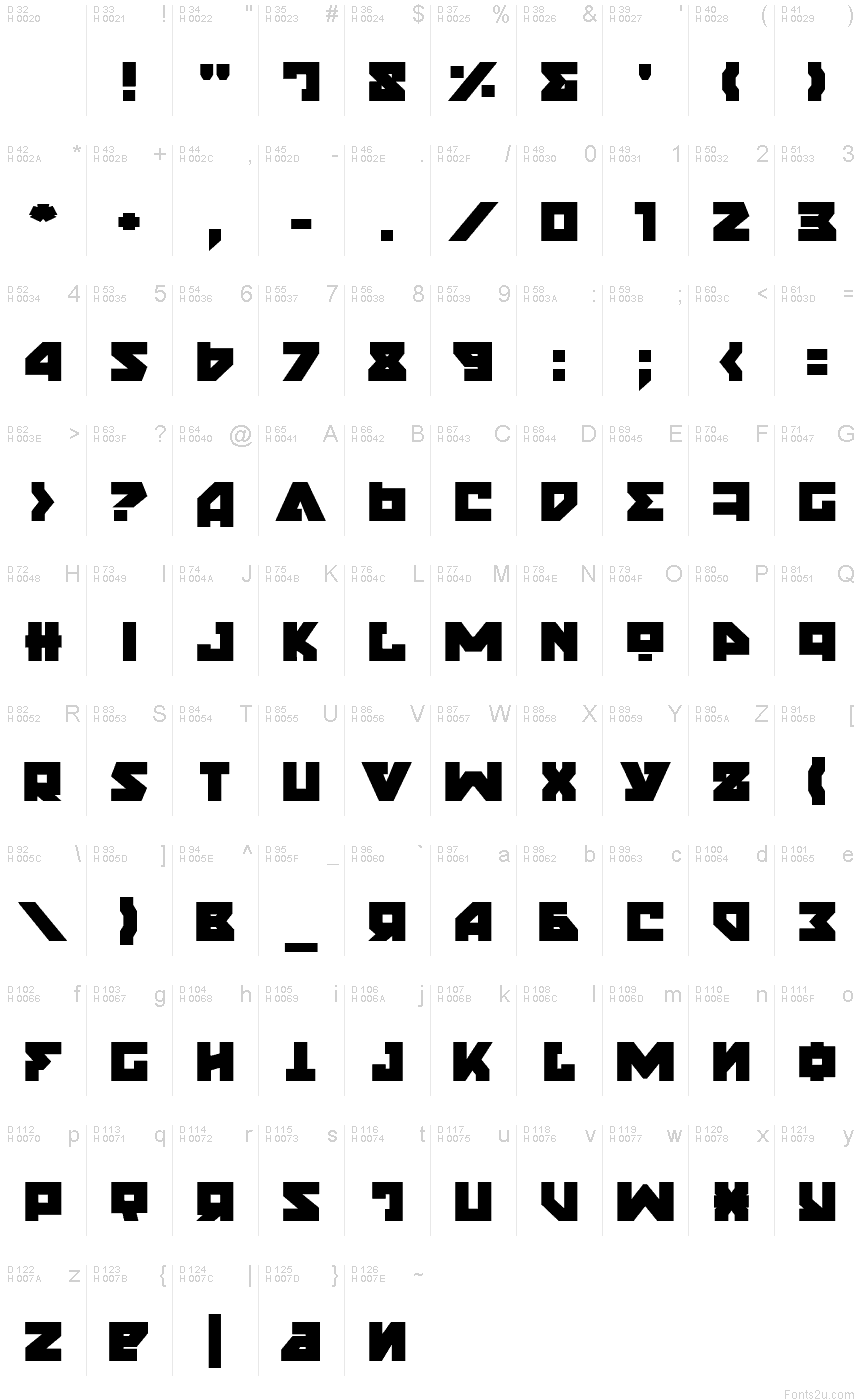
Nyet Extra Bold od Iconian Fonts to darmowy, wyświetlaczowy krój pisma w stylu rosyjskim, wyróżniający się ostrymi, geometrycznymi formami i zdecydowanymi cięciami ukośnymi, które zamieniają każdą literę w zwarty blok. Powtarzające się wycięcia i kwadratowe kąty nadają mu szablonowy rytm, sprawiając wrażenie, jakby każdy znak był zbudowany z solidnych płyt o ściętych rogach.
Nyet Extra Bold świetnie sprawdza się w tytułach plakatów, opakowaniach muzycznych, logotypach gier, ulotkach i wyrazistych szyldach, gdzie pocięta geometria może stanowić główny element układu. Wnosi również ostry akcent do okładek płyt, layoutów redakcyjnych i grafik klubowych, które wymagają surowego, konstrukcyjnego charakteru.
Nyet Extra Bold